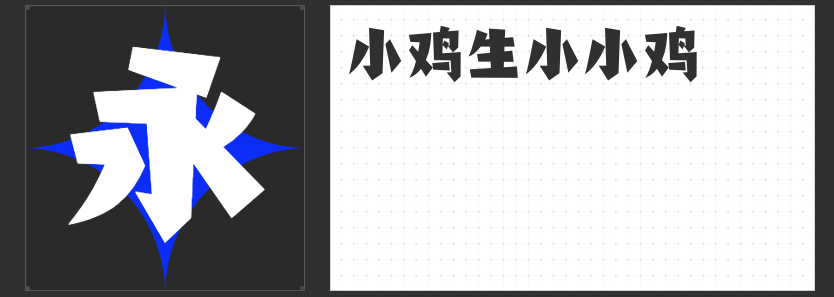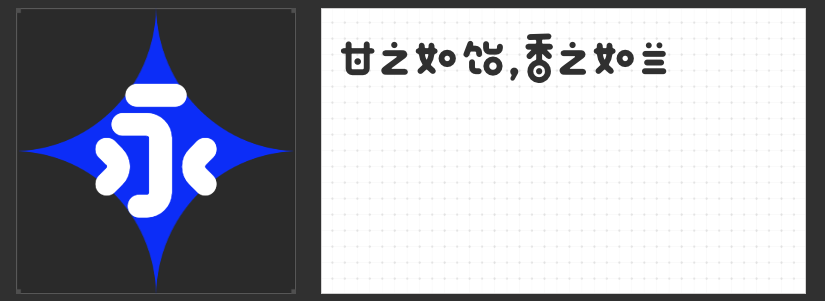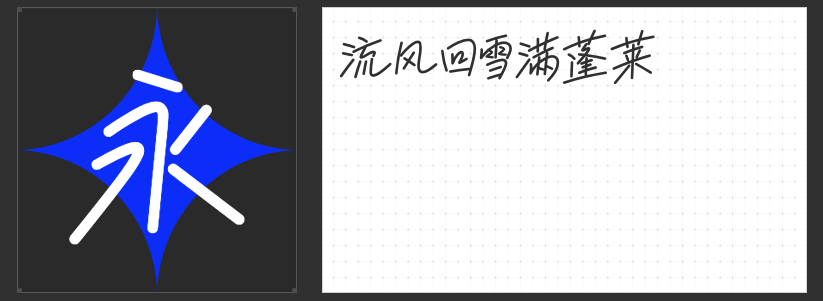
萌动视界!四款设计师必备的创意字体推荐
在视觉设计的宇宙中,字体是点燃创意的火种。当常规字体无法满足脑洞大开的创意需求时,以下四款充满生命力的创意字体,将以突破性的设计语言,为海报、品牌、插画注入灵魂级的视觉表达。
1.创客贴软糖体
如棉花糖般蓬松的笔画,软糖体将Q弹质感注入文字肌理。圆润无棱角的轮廓自带亲和力,仿佛能捏出甜腻汁水的饱满造型,尤其适合儿童产品包装、甜品店视觉或社交APP界面。其布白设计如软糖拉丝般舒展,在标题应用中能瞬间营造轻松愉悦的治愈系氛围,让文字成为可触摸的甜蜜符号。
2. 贴仔流风体中粗
这款字体完美捕捉了手写体「似齐非齐」的呼吸感,粗犷笔触间透出设计师的果决性格。中粗字重既保留手写温度,又确保阅读清晰,特别适配潮牌主视觉、音乐专辑封面或个性店铺招牌。笔画收笔处的飞白处理,如同书法中的枯笔技法,在规整排版中注入不羁的生命力。
3. 励字山中精灵简
拙朴线条勾勒出原始森林的奇幻生灵,这款字体将儿童简笔画的天真基因注入现代设计语境。非对称的布白设计打破常规韵律,却通过圆润转折达成奇妙平衡,尤其适合绘本标题、儿童教育产品或二次元游戏界面。每个笔画都藏着惊喜彩蛋,等待观察者发现萌动细节。
4. 励字俊林简
以「竹叶清风」为灵感源泉,这款字体将传统书法韵致解构成现代萌系语言。圆弧转角如满月温润,留白空间暗合水墨韵律,在电商促销页、文化类海报或国风包装中能完美调和商业气息与艺术质感。其「萌而不幼」的设计哲学,为传统书法现代化提供全新解题思路。
这四款字体如同设计师的「视觉玩具箱」,既能创造软萌治愈的童话王国,也能构建个性张扬的潮流舞台。从儿童绘本到先锋艺术展,从商业海报到文化周边,它们用突破性的设计语言证明:文字不仅是信息载体,更是能直击人心的情感雕塑。立即将这些创意火种加入你的设计资源库,让想象力在字间燃烧!